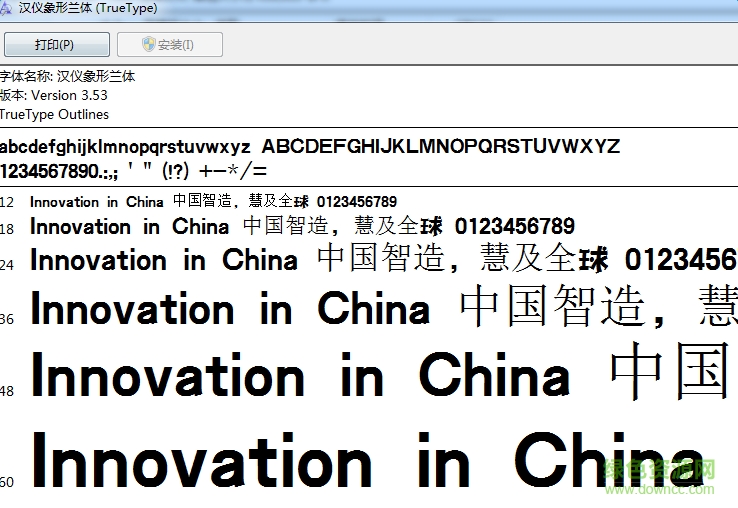
漢儀象形蘭體是一款漢儀字庫(kù)中的個(gè)性字體,該字體可以廣泛應(yīng)用于廣告設(shè)計(jì)、宣傳海報(bào)、ppt、影視制作以及任何使用文字的領(lǐng)域,有需要的朋友可以免費(fèi)下載收藏。
漢儀象形蘭體是漢儀字體庫(kù)中的一款個(gè)性字體,該字體非常端莊大方,適用于多個(gè)方位,有需要的朋友可以來(lái)綠色資源網(wǎng)下載使用!